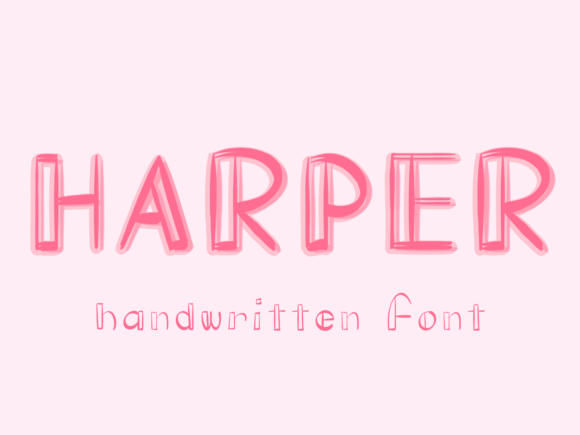
Harper
Att hitta rätt designelement kan vara utmanande, men Harper erbjuder en exceptionell samling som omedelbart lyfter ditt arbete.
Tillverkad med precision, ger Harper rena vektorer, smidig typografi och en kommersiell licens för sinnesfrid.
Oavsett om du skapar POD-produkter (Print on Demand), bröllopsinbjudningar eller grafik för sociala medier, är Harper ett perfekt val.